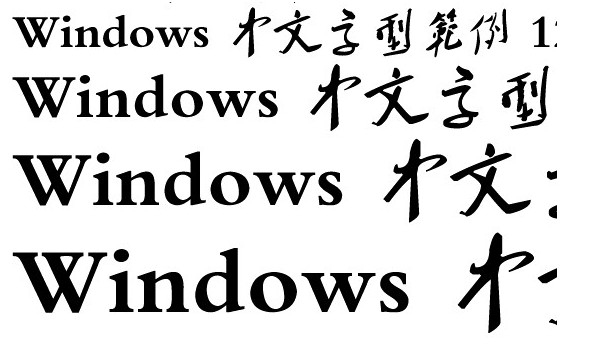
毛澤東草書字體
毛澤東草書字體是一款偉大領袖毛主席的字體,毛主席草書風格雄渾,力道蒼勁,在很多設計眼里都是電腦必備字體,趕緊下載吧。
毛澤東是老一輩無產(chǎn)階級革命家,當代杰出詩人。他的詩詞是革命現(xiàn)實主義與革命浪漫主義相結(jié)合的典范,繼承和發(fā)展了古詩詞的傳統(tǒng),創(chuàng)造了革命的政治內(nèi)容和完美的藝術形式高度統(tǒng)一的詩篇。它思想內(nèi)容強,藝術境界高,在人民大眾中廣為傳頌,給人以強大的鼓舞力量。中國草書經(jīng)廣大書家的創(chuàng)造,集眾美于一體,有豐富的美學內(nèi)涵,達到很高的藝術境界。它有氣勢、有力度、有神韻,生動活潑,柔韌雄強,彰顯了中華民族精神。